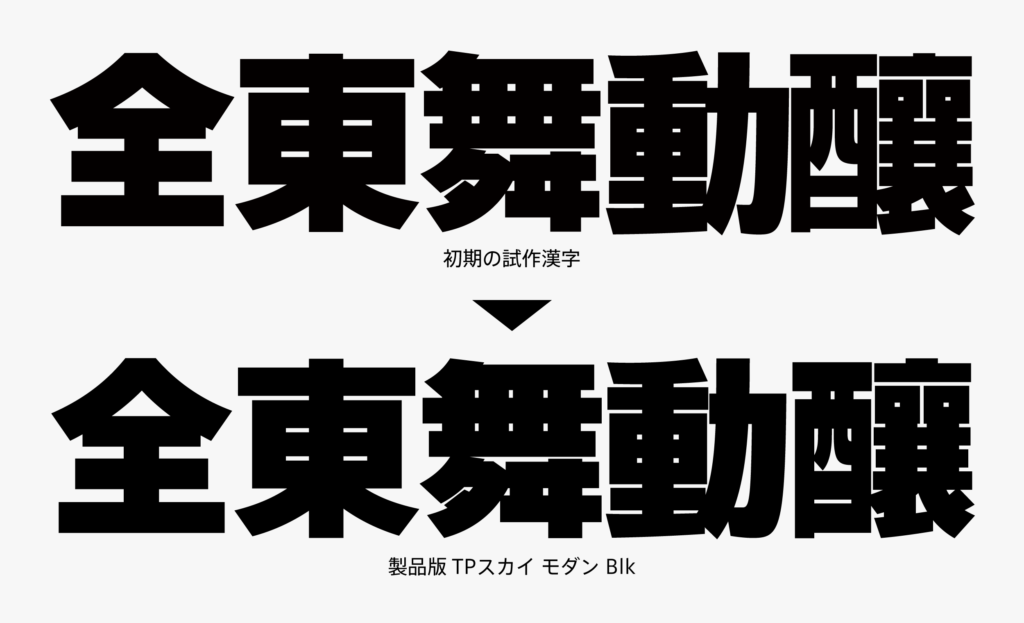
TPスカイ モダン Blk 開発ストーリー 02「骨格・太さ」
TPスカイ モダン Blkの制作は、TPスカイ ローコントラスト Bから骨格を広げて筆画を太くする作業でした。画数の少ない漢字は骨格を広げるゆとりがあるのですが、画数の多い漢字は太い線が混み合うので筆画を動かす余地が限られています。両者が一つの組版の中に混在しても揃って見えるように試作を重ねながら骨格の広げ具合を調整しました。
スタンダードな和文書体の中では特に太いウエイトを目指していました。フィットフォントなどでの利用も想定して、モダン Blkの試作欧文だけでなく他の欧文書体とも組み合わせたサンプルを作り、TPスカイローコントラスト Bから数段太いウエイトにも合わせられることを確認しています。
画数の多いグリフを太くするとき、主要な筆画だけを太く・その他の筆画を細くして混雑を避ける手法がありますが、モダン Blkはこの太細の差を控えめにしてなるべくフラットに見えるよう作っています。これはTPスカイ ファミリー(特にローコントラストのシリーズ)のデザイン方針であり、その他の点においても「TPスカイシリーズの一員である」というのは抑えるべき重要なポイントでした。